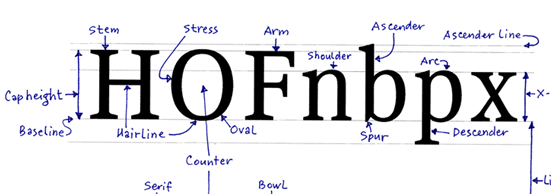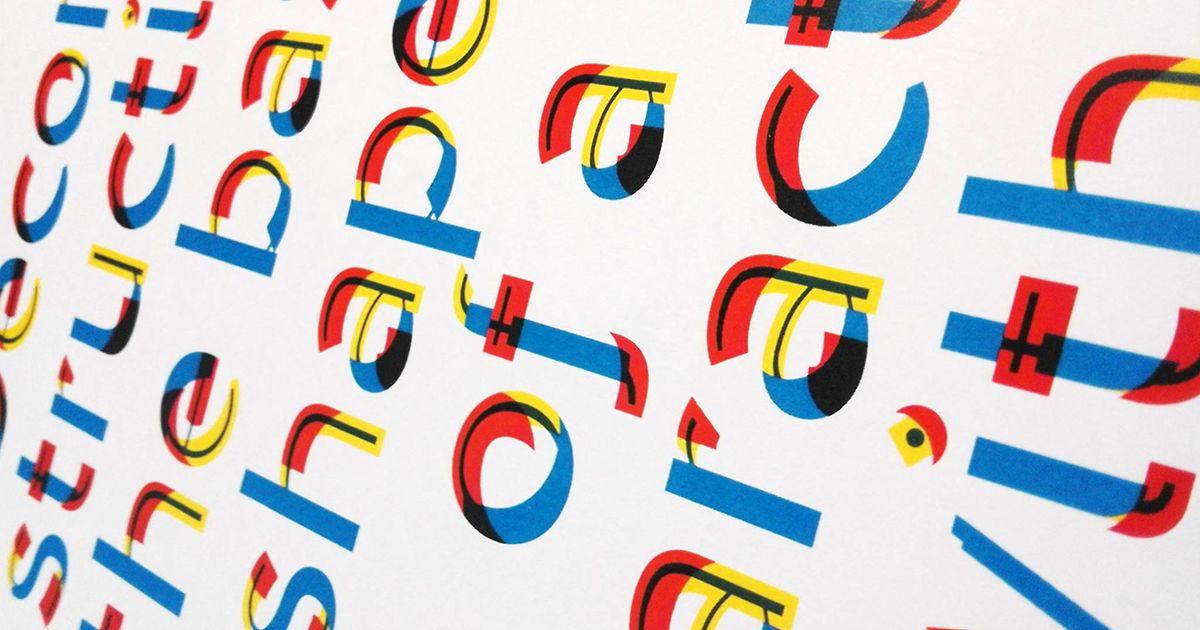
Cùng tìm hiểu về chúng ngay bây giờ, vì những phông chữ có khả năng biến đổi này đang ngày càng phát triển và phổ biến hơn.
Sự phát triển của những typeface mới gắn liền với sự phát triển của công nghệ hiện tại để có thể thiết kế và tái sản xuất chúng. Mặc dù ý tưởng về Parametric Font và Variable Font đã xuất hiện từ những năm 1970, nhưng phải tới gần đây, nhờ vào công nghệ, designer mới có thể thiết kế những typeface có khả năng biến đổi hình dạng. Cả hai thể loại type này đều khác xa với định nghĩa về typeface thông thường là mang tính hoàn thiện, ổn định và không thay đổi. Thay vào đó, định dạng linh hoạt của chúng cho phép một mức độ ngẫu nhiên và đầu vào người dùng có được kết quả phù hợp nhất.
Sau đây là một bài học từ vựng nhỏ dành cho những ai không chuyên: Generative typeface (hoặc Variable typeface) là những typeface cho phép một file font chữ có thể trở thành nhiều font khác nhau, với vô số weight(1), widths(2) và các thuộc tính typography đa dạng khác. Mặt khác, Parametric font vận hành bằng một tập hợp những thông số chính xác của từng kí tự, nhờ đó tạo ra những điều chỉnh đa dạng về X-height(3), stroke width(4) và letter width(5).
Variable Font giúp cho Responsive Web Design (Thiết kế web đáp ứng) trở nên khả thi hơn, nó cho phép các kí tự chữ tự động thay đổi để phù hợp với giới hạn của các màn hình và trình duyệt khác nhau. FIT Hebrew là một ví dụ điển hình của Variable Font:
Một ví dụ khác tương tự là FF Beowolf, một trong những typeface đầu tiên đại diện cho Variable Font xuất hiện vào khoảng những năm 1980, khi tất cả các hình thức chữ trên nền tảng kỹ thuật số đang ở giai đoạn khởi đầu. Tới năm 1990, font chữ này đã được mua lại bởi Bảo Tàng Nghệ Thuật Hiện Đại để sử dụng cho bộ sưu tập nghệ thuật chủ đề vĩnh cửu. Để thiết kế nó, designer Just van Rossum và Erik van Blokland đã sửa đổi bản lập trình chuẩn bằng file PostScript để tạo ra những biến đổi ngẫu nhiên xảy ra sau khi các kí tự font được cài đặt. Những kí tự chữ này sẽ thay đổi khi chúng được in ra, tạo nên những kết quả không thể đoán trước mỗi lần.
Về sau, các nhà thiết kế chuyên nghiên cứu về Generative Type bắt đầu phát triển những dòng code và thuật toán cần thiết để hoàn thiện nó. Nhưng phải đến năm 2016 thì Generative Type mới có một bước nhảy vọt để trở nên phổ biến hơn khi Google, Adobe, Microsoft và Apple đã cùng tham gia phát triển OpenType Font Variations. Công nghệ này giúp thêm vào trong font một bộ glyph hoặc từng glyph(6) riêng lẻ lên tới 64,000 biến thể về weight hoặc width khác nhau và giúp xác định vị trí rõ ràng trong không gian thiết kế trong từng trường hợp cụ thể (bold(7) hoặc condensed(8)).
Để hiểu rõ hơn về ứng dụng của công nghệ này, hãy cùng xem qua bộ nhận diện The New School của thành phố New York được tái thiết kế vào năm 2016, được thiết kế bởi thành viên của Pentagram, Paula Scher. Bà đã sử dụng một Variable Typeface thiết kể bởi founder của Typotheque, Peter Bil’ak. Trong đó, typeface độc nhất, Neue, được chi phối bởi một thuật toán tuỳ chỉnh, nó thay thế regular width(9), extended width(10), và extra extended width(11) từ một font duy nhất chỉ trong một khối type. Kể cả chính logo cũng được thiết kế để có thể thay đổi bố cục một cách linh hoạt.
Hệ thống Parametric thì hoạt động khác một chút so với Variable Font, bằng cách thêm vào (tương tự như biến đổi hình dạng) từ hai hoặc nhiều thiết kế gốc cho từng kí tự. Các hệ thống tiên tiến và phức tạp nhất hiện nay có thể tạo nên nhiều bộ font từ một font gốc duy nhất.
Khái niệm Parametric được bắt nguồn từ toán học, trong đó nó mô tả các phương trình sử dụng một hoặc nhiều tham số độc lập để biểu thị tọa độ xác định của một đối tượng hình học hoặc bề mặt cong của nó.
Parametric Type lần đầu xuất hiện trong giới design vào năm 1977 khi nhà toán học Donald Knuth giới thiệu Metafont, một ngôn ngữ lập trình sử dụng các phương trình hình học để xây dựng các mẫu chữ của nó. Đối với các hệ thống chữ, việc mã hóa các thông số của từng kí tự cho phép người dùng áp dụng toàn bộ các thay đổi cho từng thành phần của một mẫu chữ - chẳng hạn như về độ rộng (width) hoặc có chân chữ hay không (serif(12)) - dựa trên các giá trị thuật toán được xác định bởi type designer. Việc mã hóa cho phép các nhà thiết kế điều chỉnh các mẫu chữ một cách nhanh chóng bằng cách sử dụng thanh trượt để có được bản xem trước tức thì về thay đổi của mẫu chữ. Hãy thử nhìn vào font Antique Gothic, một ví dụ về Parametric Font đương đại.
Antique Gothic được thiết kế bởi Prototypo, cùng với Metapolator, là một ví dụ tốt về dự án thử nghiệm với Parametric Type. Dan Rhatigan, quản lý cấp cao của Adobe Type xem Parametric Type như minh chứng cho ý tưởng rằng một typeface không nhất thiết phải được chỉnh sửa cho đến khi nó được giao cho khách hàng. “Tôi cho rằng các công cụ này được nhóm lại chung với những gì mà một vài nhà thiết kế đang cố gắng thực hiện với việc cung cấp các web font từ các tệp nguồn, thay vì cung cấp những font đã được tạo sẵn hoặc sản xuất,” anh ấy nói.
Những font được vẽ bởi các công cụ truyền thống có sẵn đều có thể đưa vào Metapolator bằng cách sử dụng định dạng Unified Font Object (UFO) và phần mềm sẽ tự động tạo ra vô số những biến thể hình dạng khác nhau. Với công cụ này, một type designer vẫn đóng vai trò quan trọng trong quá trình, tạo ra những thay đổi và nói rằng, “OK. Với kích thước này chúng ta có thể làm cho nó dày hơn. Khi sử dụng chữ với kích thước to hơn, nó sẽ có độ dày như thế này.” Nói cách khác, đây không phải là một hệ thống ngẫu nhiên, mà một chuyên viên thiết kế sẽ sử dụng kiến thức của mình để xác định phạm vi hiển thị của typeface đó.
“Cần rất nhiều lần thử nghiệm thủ công cho các biến thể typography khác nhau, điều mà phần mềm như Prototypo có thể tự động thực hiện một cách dễ dàng,” Scher nói. “ Điều này giúp bạn tiết kiệm được một vài giờ làm việc: Bạn có thể thấy một typeface ở các độ rộng khác nhau, có chân (serif) hoặc không có chỉ qua một vài thao tác nhanh chóng. Khả năng thành công là rất lớn, bởi vì bạn có thể chọn bất kỳ phông chữ nào và khám phá toàn bộ chiều rộng của kiểu chữ trong đó.
Chú thích:
- Weight: độ đậm của chữ
- Width: bao gồm stroke width và letter width
- X-height: khoảng cách từ baseline đến midline
- Stroke width: độ rộng của nét chữ
- Letter width: độ rộng của chữ
- Glyph: hình ảnh của một chữ
- Bold: chữ đậm
- Condensed: chữ có độ rộng nhỏ hơn trong một family font
- Regular width: chữ có độ rộng thường
- Extended width: chữ có độ rộng lớn hơn
- Extra extended width: chữ có độ rộng lớn nhất
- Serif: chữ có chân